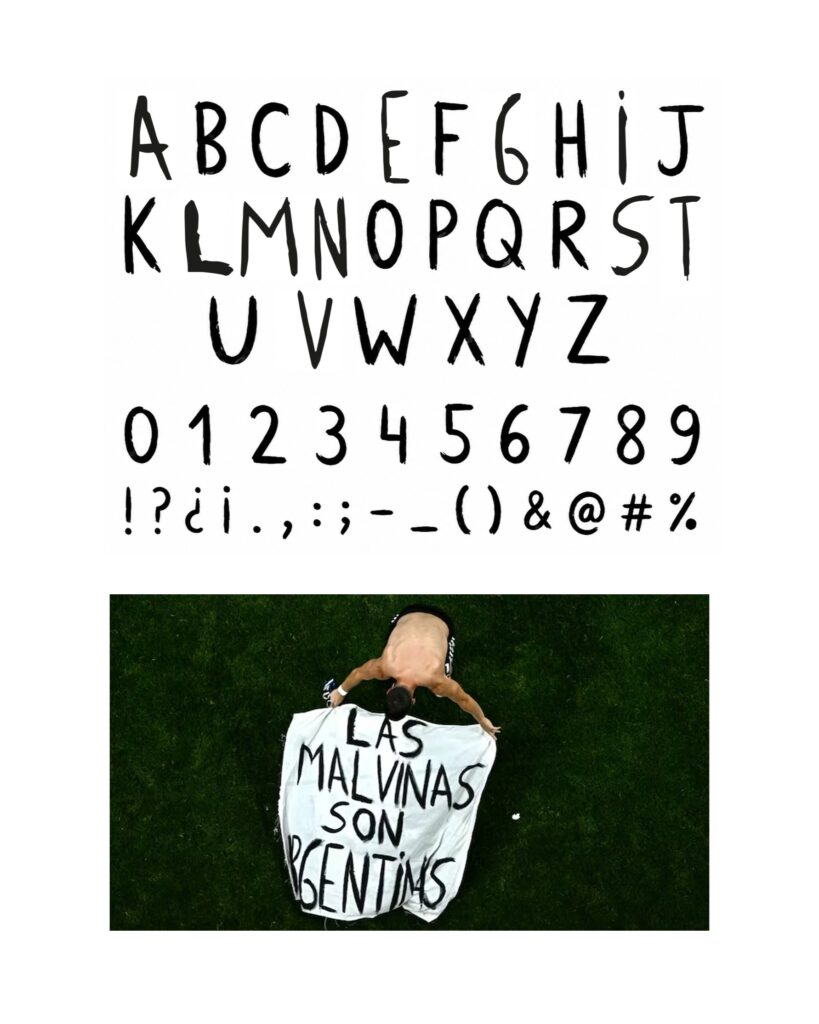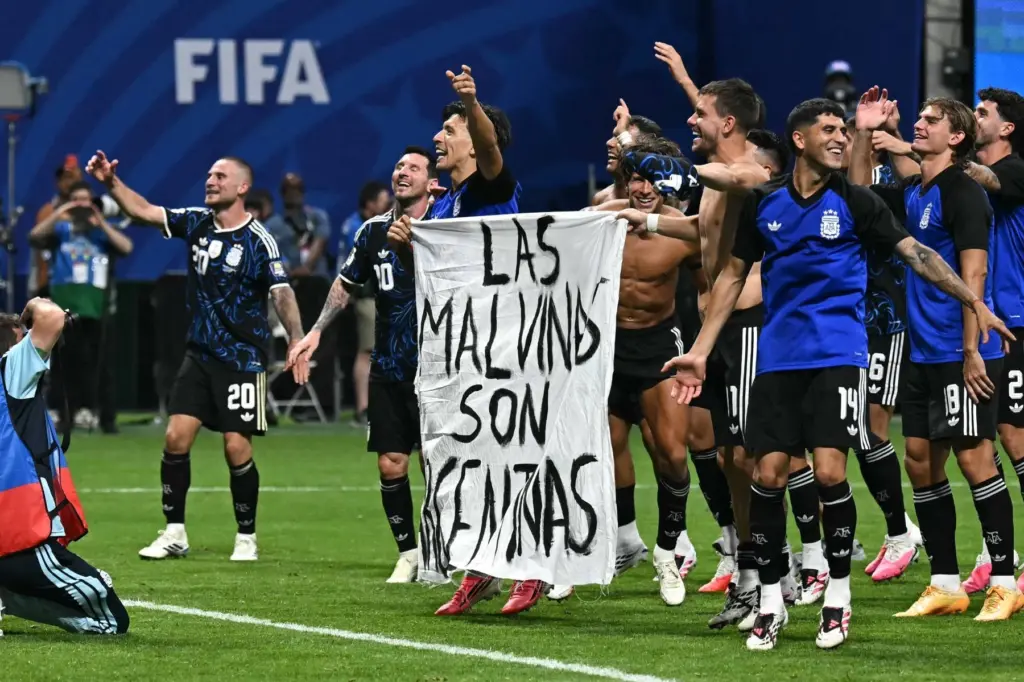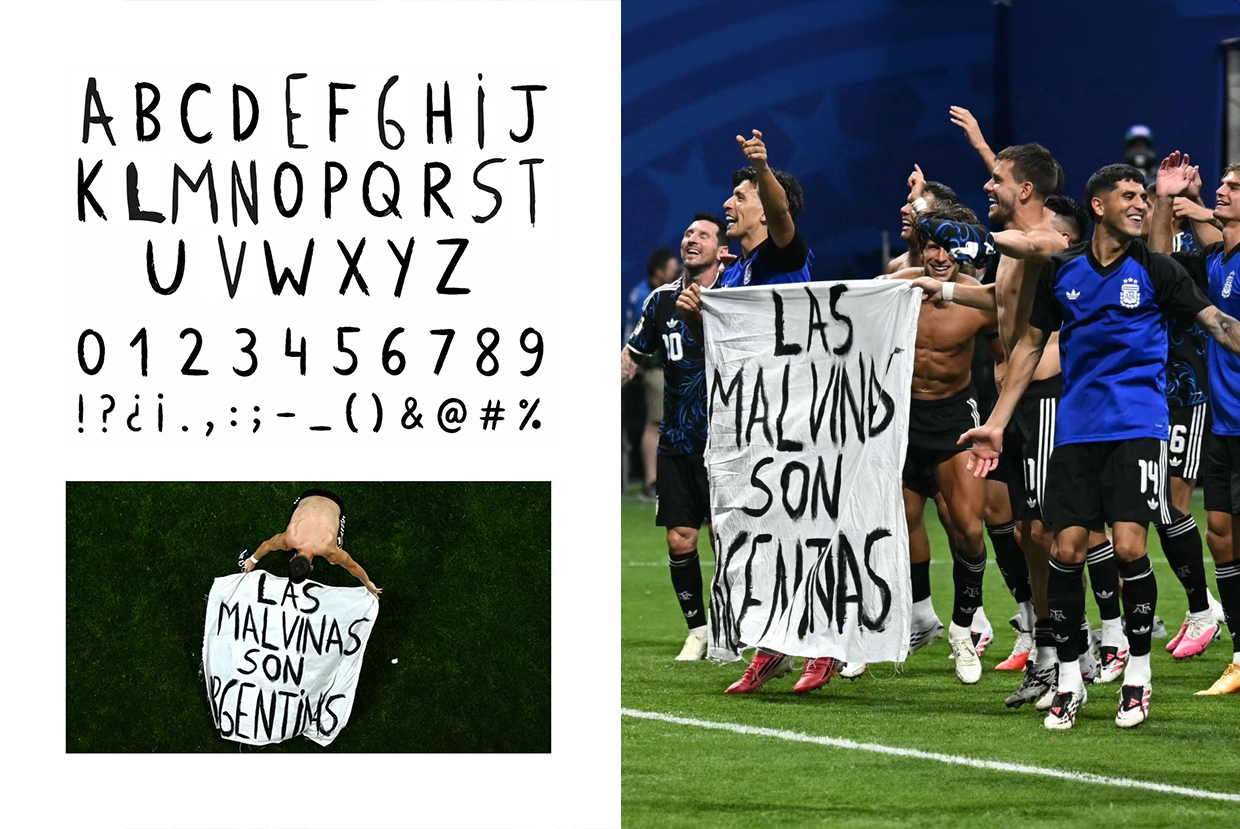
Một khoảnh khắc đầy sức nặng chính trị tại trận bán kết World Cup 2026 của Argentina giờ đây đã tìm được một “sân đấu” mới – ngay trong menu font chữ.
Tấm biểu ngữ vẽ tay được giương lên sau chiến thắng của Argentina trước đội tuyển Anh đã được chuyển thành Malvinas Sans, một typeface miễn phí lưu giữ nguyên vẹn tinh thần của khoảnh khắc ấy qua từng con chữ không hoàn hảo.
Tấm biểu ngữ xuất hiện sau khi Argentina đánh bại Anh 2–1 tại Atlanta vào ngày 15/7. Trong lúc ăn mừng, một số cầu thủ đã cầm tấm banner do người hâm mộ đưa với dòng chữ “Las Malvinas son Argentinas” (Quần đảo Malvinas thuộc về Argentina”), đề cập đến quần đảo mà phía Anh gọi là Falkland.
Hình ảnh nhanh chóng trở thành một trong những khoảnh khắc mang màu sắc chính trị rõ nét nhất giải đấu World Cup lần này. Anh đã đề nghị FIFA xem xét vụ việc, trong khi cơ quan quản lý bóng đá thế giới mở cuộc điều tra nhằm xác định thông điệp này có vi phạm quy định cấm khẩu hiệu chính trị tại các trận đấu hay không.
Argentina và Vương quốc Anh từ lâu vẫn tranh chấp chủ quyền đối với quần đảo này – nơi từng là tâm điểm của cuộc chiến Falklands/Malvinas năm 1982. Chính bối cảnh lịch sử ấy khiến tấm biểu ngữ mang ý nghĩa vượt xa kết quả của một trận bán kết bóng đá.
Nghệ sĩ Argentina Juan Manuel Pelillo, được biết đến trên mạng với tên @juanma_artwork, sau đó đã biến chính nét chữ trên tấm banner thành một typeface kỹ thuật số. Sử dụng nền tảng tạo font Calligraphr, anh phát triển số ký tự ít ỏi xuất hiện trên biểu ngữ thành một bộ font hoàn chỉnh hơn gồm chữ cái, chữ số và ký hiệu.
Font được đặt tên là Malvinas Sans. Dù mang chữ “Sans”, những nét chữ gồ ghề và hình dạng thiếu nhất quán của nó khác xa vẻ chỉn chu của một sans serif thương mại. Nhưng chính sự không hoàn hảo ấy lại tạo nên sức hút: những nét cọ vội vàng, khoảng cách chữ không đều và cảm giác khẩn trương của tấm biểu ngữ gốc vẫn được giữ lại.
Pelillo mô tả đây là một “typeface sinh ra từ thứ vốn được cho là phải bị cấm”, xem dự án như một công cụ của ký ức và sự phản kháng hơn là sự tôn vinh xung đột. Theo anh, việc hạn chế một câu nói không khiến tranh chấp phía sau nó biến mất, mà thậm chí có thể khiến vấn đề được chú ý nhiều hơn.
Dự án nhanh chóng lan truyền tại Argentina. Bài đăng giới thiệu của Pelillo trên Instagram nhận được hơn 50.000 lượt thích chỉ trong vài ngày, với nhiều bình luận gọi đây là một typeface mang tính quốc gia, được tạo nên từ ký ức, đam mê và tinh thần phản kháng.